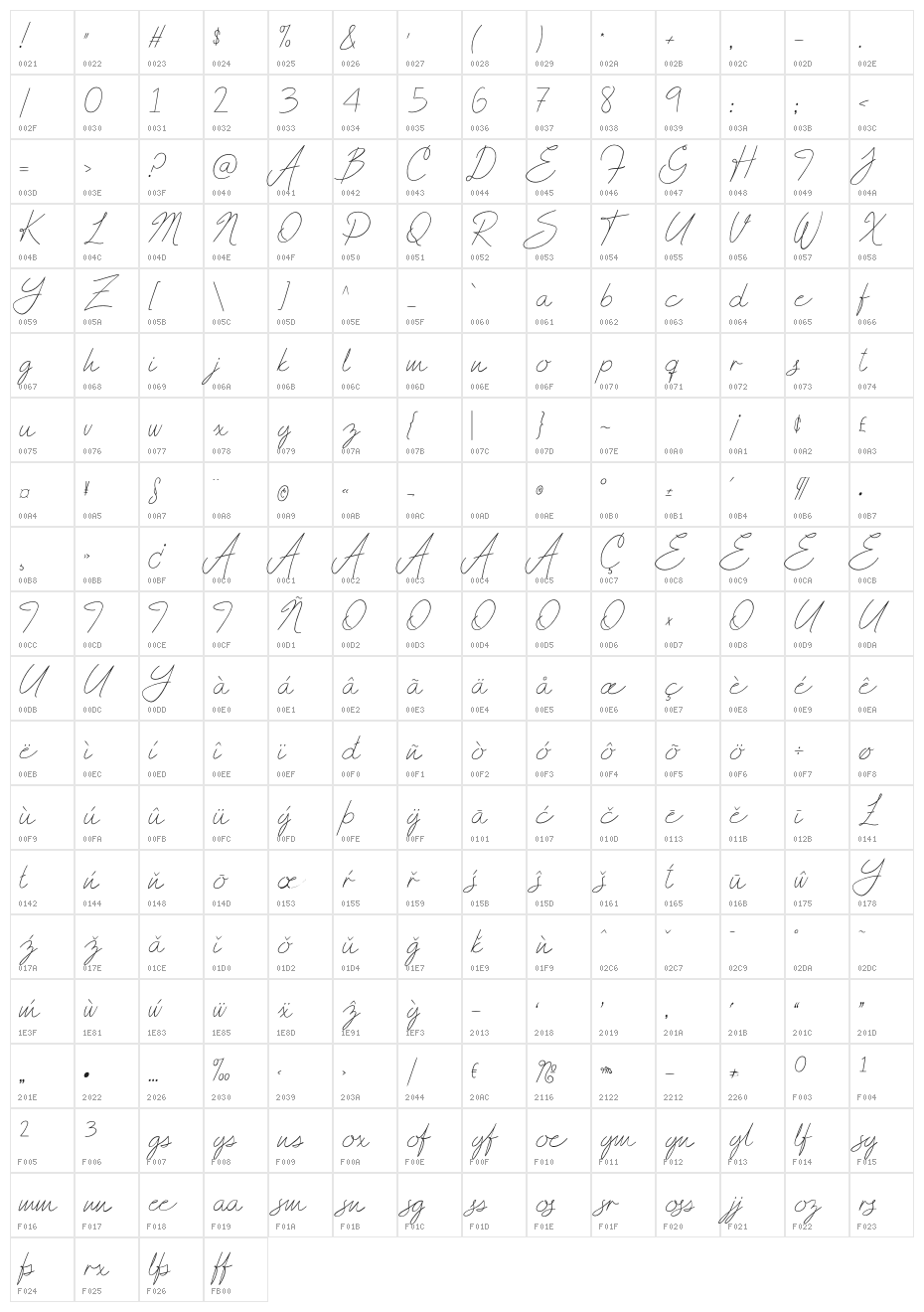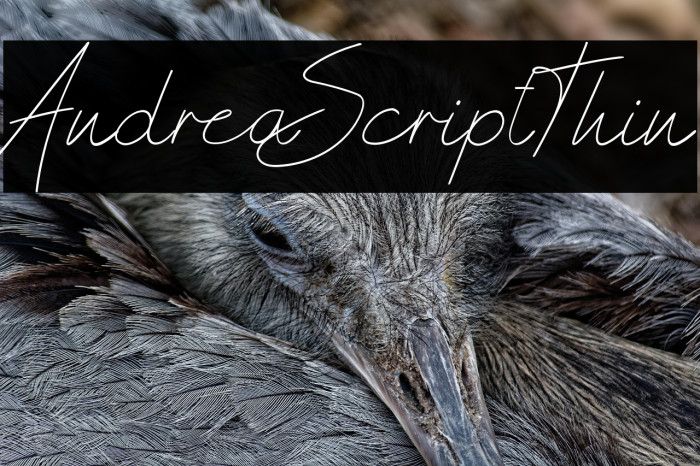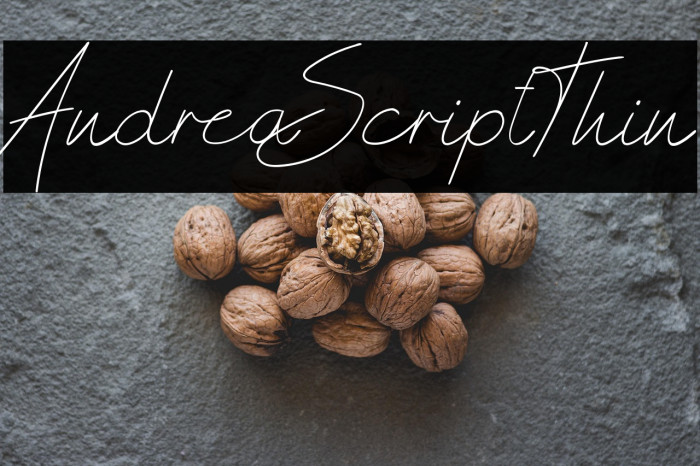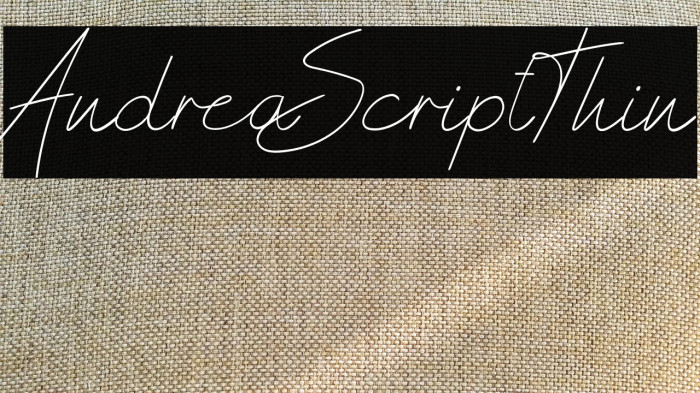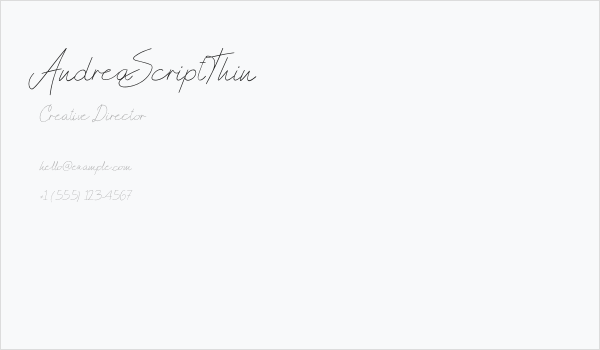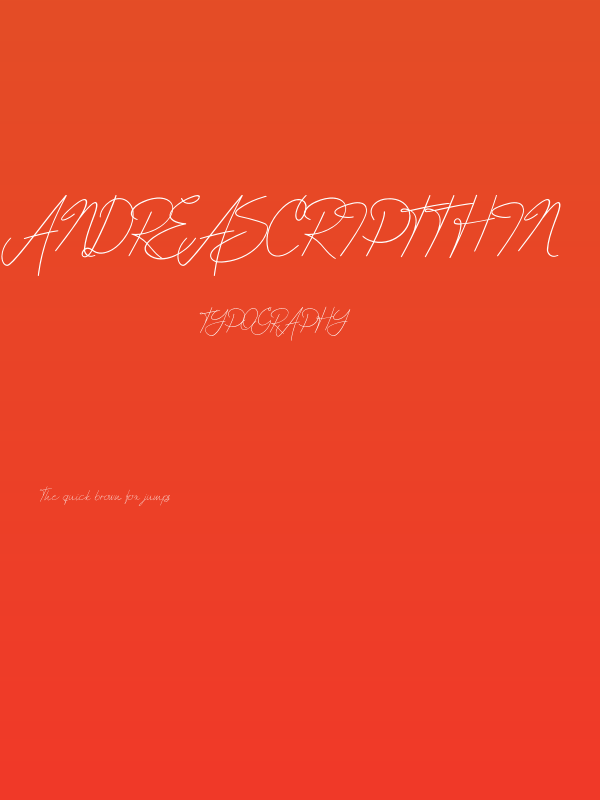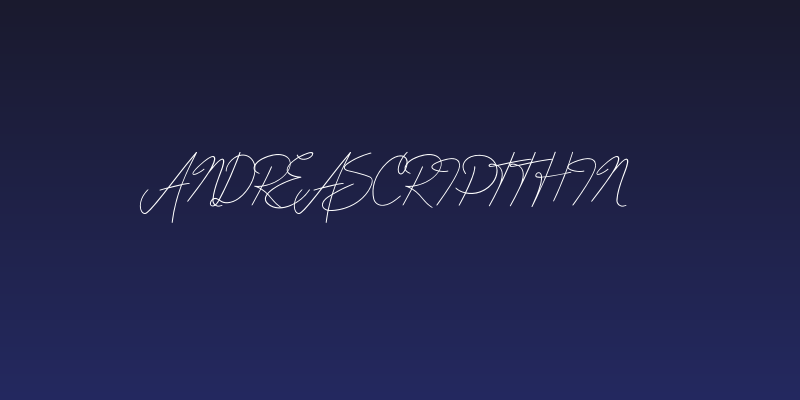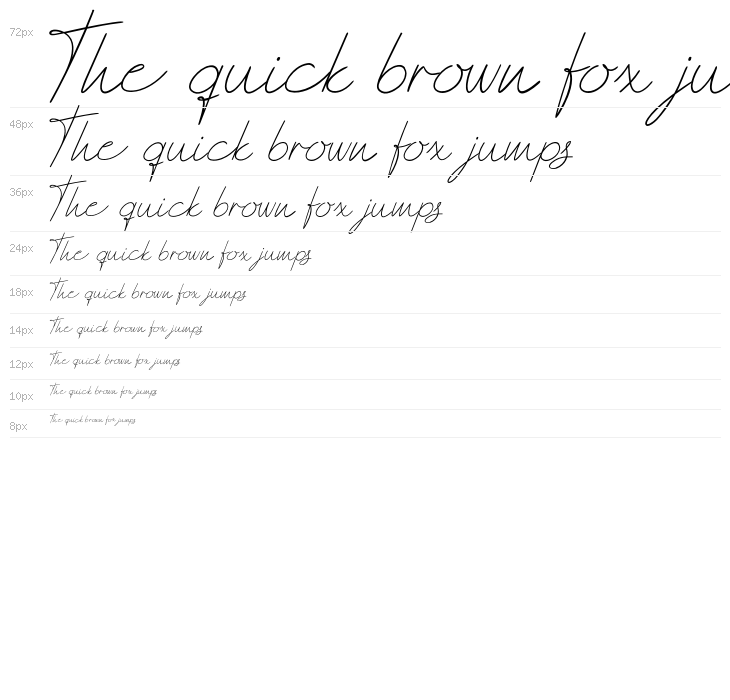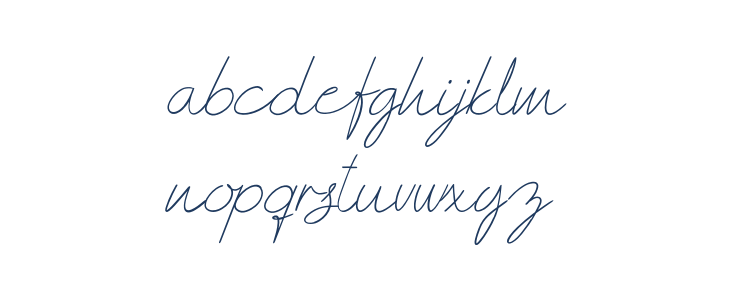
AndreaScriptThin Font
| Stile generale | Elegant, Modern |
| Caso d'uso | Logos, Invitations, Decorative text |
| Progetti proposti | Ideal for wedding invitations, elegant branding, personal stationery, and artistic projects. |